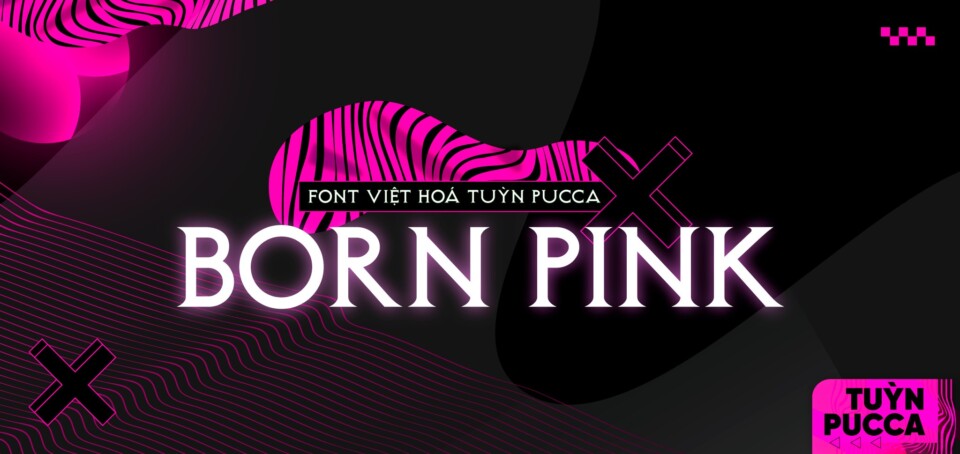
Tải Font việt hóa TP Born Pink – Font chữ nghệ thuật cho thiết kế sáng tạo
Giới thiệu về Font việt hóa TP Born Pink trong thiết kế
Trong thế giới đồ họa hiện đại, việc tìm kiếm một bộ Font Chữ mang đậm phong cách trẻ trung và cá tính là điều rất quan trọng. Font việt hóa TP Born Pink chính là lựa chọn hoàn hảo cho những ai yêu thích vẻ đẹp hiện đại, mềm mại nhưng không kém phần nổi bật. Bộ font này được lấy cảm hứng từ các trào lưu âm nhạc và văn hóa đại chúng, mang đến hơi thở mới lạ cho mọi dự án từ làm slide thuyết trình đến thiết kế poster trường học.
Đặc điểm nổi bật của bộ font nghệ thuật
Được thiết kế với các đường nét thanh mảnh và những đường cong cách điệu, font chữ này tạo cảm giác uyển chuyển và linh hoạt. Đặc biệt, bản việt hóa đã được tối ưu hóa hoàn toàn để hiển thị chính xác các dấu tiếng Việt mà không gặp lỗi chân chữ hay khoảng cách. Điều này cực kỳ hữu ích cho các bạn học sinh và giáo viên khi muốn tạo ra những ấn phẩm truyền thông chuyên nghiệp nhưng vẫn giữ được sự gần gũi, dễ nhìn.
Cách ứng dụng Font việt hóa TP Born Pink hiệu quả
Bạn có thể sử dụng bộ font này trong nhiều ngữ cảnh khác nhau. Trong môi trường sư phạm, nó giúp các bài giảng PowerPoint trở nên sinh động hơn, thu hút sự chú ý của người xem ngay từ cái nhìn đầu tiên. Ngoài ra, các thiết kế bìa sổ tay, thiệp mừng hay áo đồng lớp cũng sẽ trở nên ấn tượng hơn rất nhiều khi có sự góp mặt của bộ chữ này.
Lưu ý khi sử dụng font trong đồ họa
Để đạt hiệu quả thẩm mỹ cao nhất, bạn nên kết hợp font này với các tông màu sáng hoặc gradient pastel. Việc sử dụng đúng kích cỡ và khoảng cách dòng sẽ giúp văn bản trở nên dễ đọc và chuyên nghiệp hơn trên mọi nền tảng.
Kết luận về bộ Font việt hóa TP Born Pink
Tóm lại, việc sở hữu bộ Font việt hóa TP Born Pink sẽ giúp bạn mở rộng khả năng sáng tạo và mang lại dấu ấn riêng cho các sản phẩm của mình. Đây là món quà tuyệt vời dành cho những ai đam mê thiết kế và đang tìm kiếm các mẫu Font Miễn Phí, Font Việt Hóa, Font việt hóa TP Born Pink chất lượng nhất hiện nay.